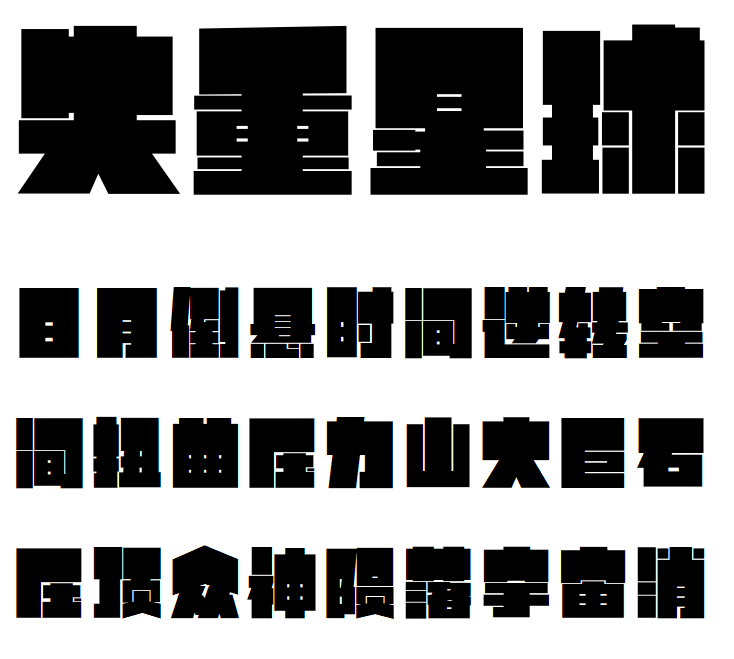
一款来自于未来的逆反差科幻字体——励字大头黑简 超级黑
我们对太空有太多幻想,对外星球的探索也在一步步实现中。越来越多的品牌与电影都讲目的地不断像太空延伸,那么一款代表未来的字体,你有幻想过它的样子吗?
空间站、磁力波、外形引力都是我们具象的幻想,将这些元素加入字体中,便是励字大头黑简。在恒星冲撞挤压形成的时空裂缝,励字大头黑简字体内部重心失衡上移,笔画则打破传统规则,粗细组合不均,转折处以直角处理后,形成的一款横平竖直、右侧笔画厚重、左边笔画极细的逆反差直线字体。